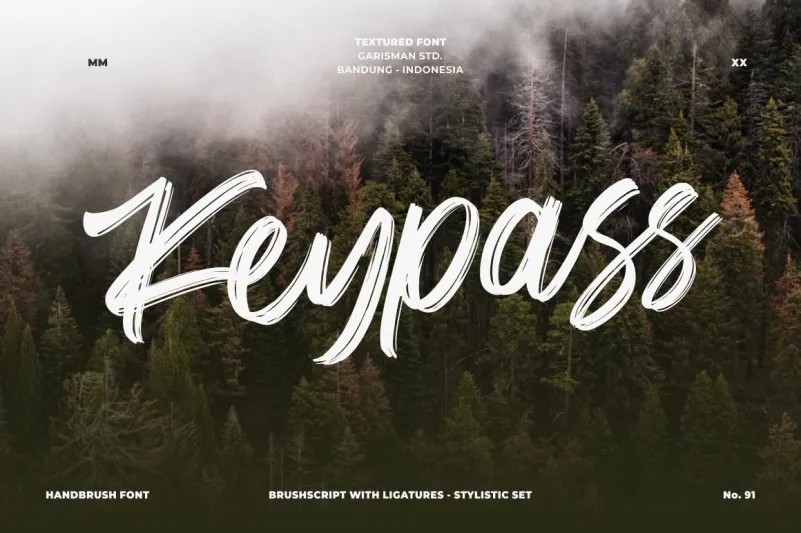
Keypass Brush Font – Fonte Grátis
Keypass Brush Font
Descubra uma nova adição à sua coleção de fonts com a Keypass Brush Font. Este elegante script foi criado pelo designer 24Design usando técnicas de escrita à mão com um pincel seco, oferecendo alternativas abundantes para atender as mais diversas necessidades de projetos. A fonte incorpora uma linha curva atrativa que ganha uma sensação urbana fresca ao mesmo tempo, garantindo um estilo elegante e sofisticado que certamente vai dar o toque final aos seus logotipos, imagens de marca, frases escritas a mão, embalagens de produtos, merchandising e postagens em mídia social. Keypass Font é uma escolha perfeita para aqueles buscando um estilo único e moderno para revolucionar suas propostas gráficas.